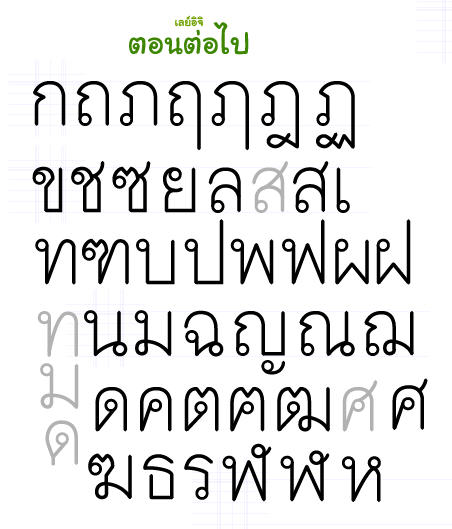
Layiji ตอนต่อไป
แนะนิดนึงนะครับ
ส เสือมันมีไส้ พอเทียบกับ ล ลิง แล้วมันหลอกตาว่า ส เสือผอมกว่า (ความจริงก็เท่ากันแหละ)
ดังนั้นตัวไหนที่มีไส้ทิ่มแทงเข้าไป ตัวนั้นเอาให้มันดูกว้างๆโปร่งๆไว้จะเป็นการดีครับ
สวยก็สวยครับ
มาตรฐานเลย์อิจี้กาแล็กซี่ 999 จริงๆ
ชอบ ภ. สำเภา ค่ะ  :22: